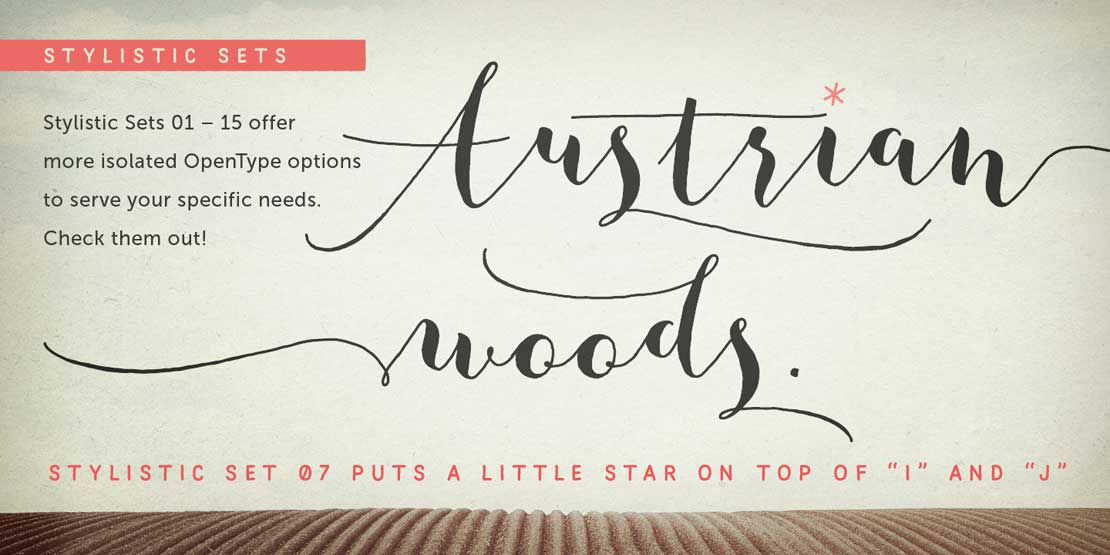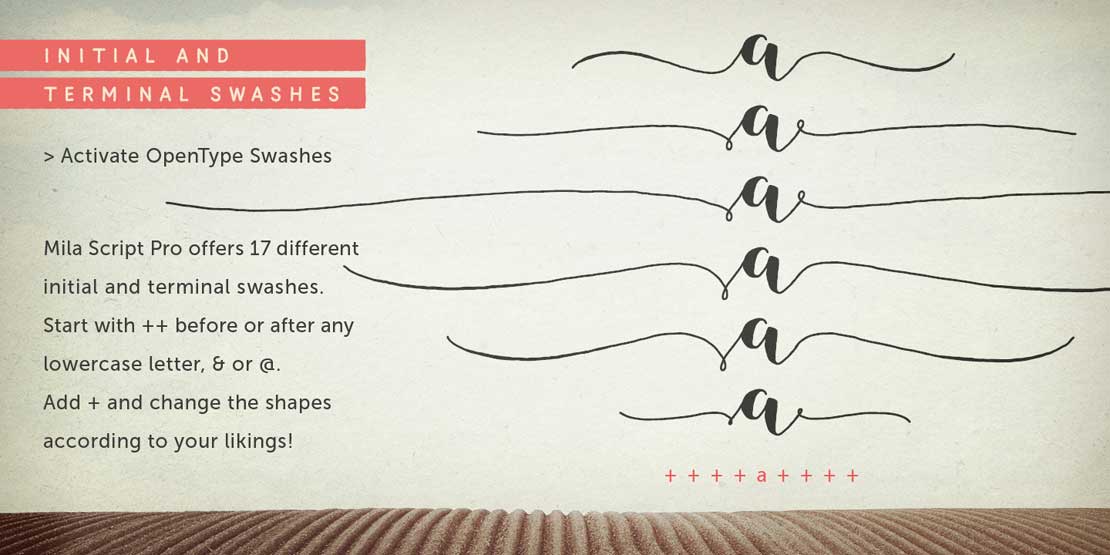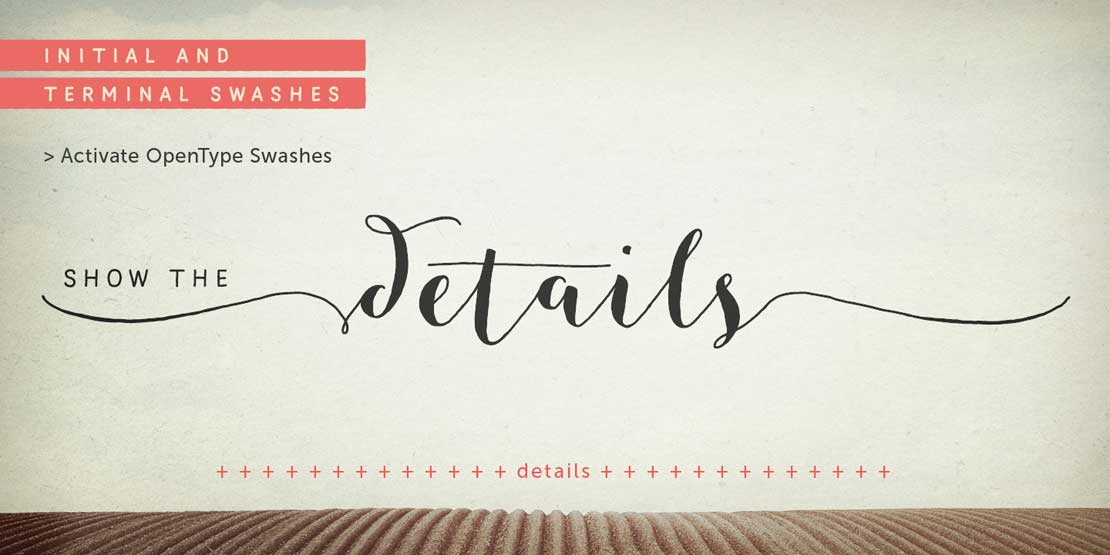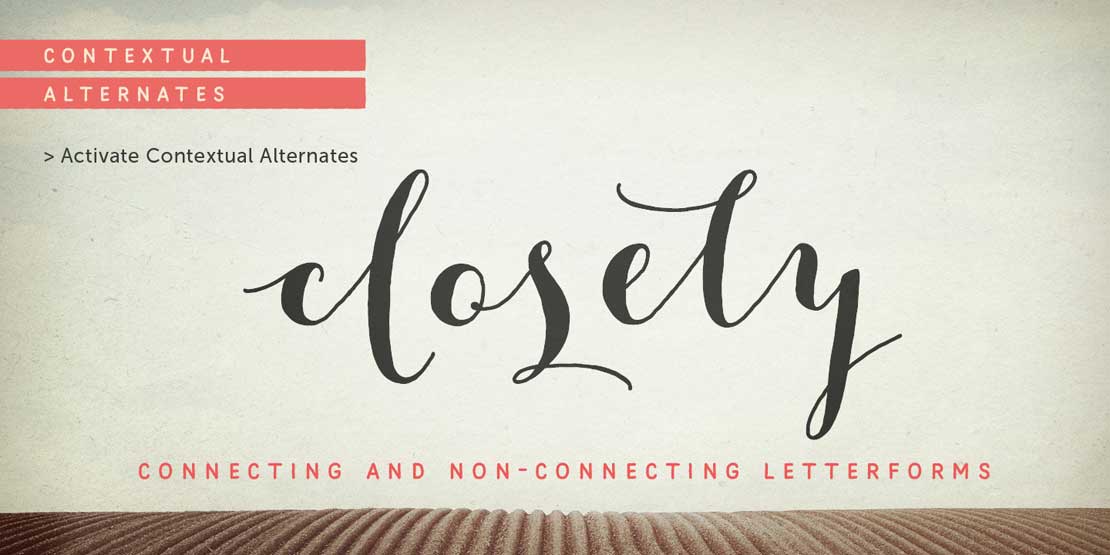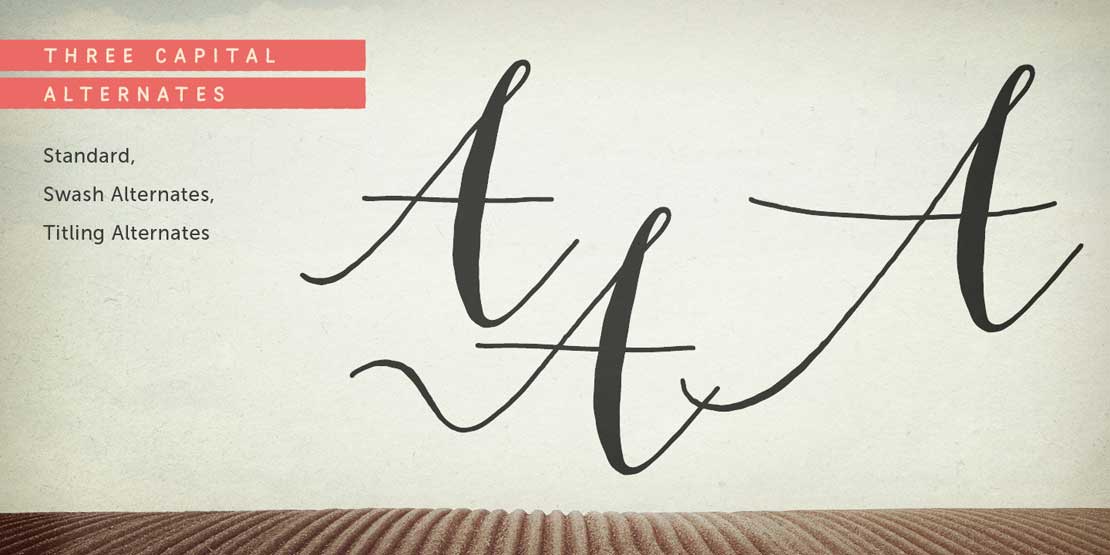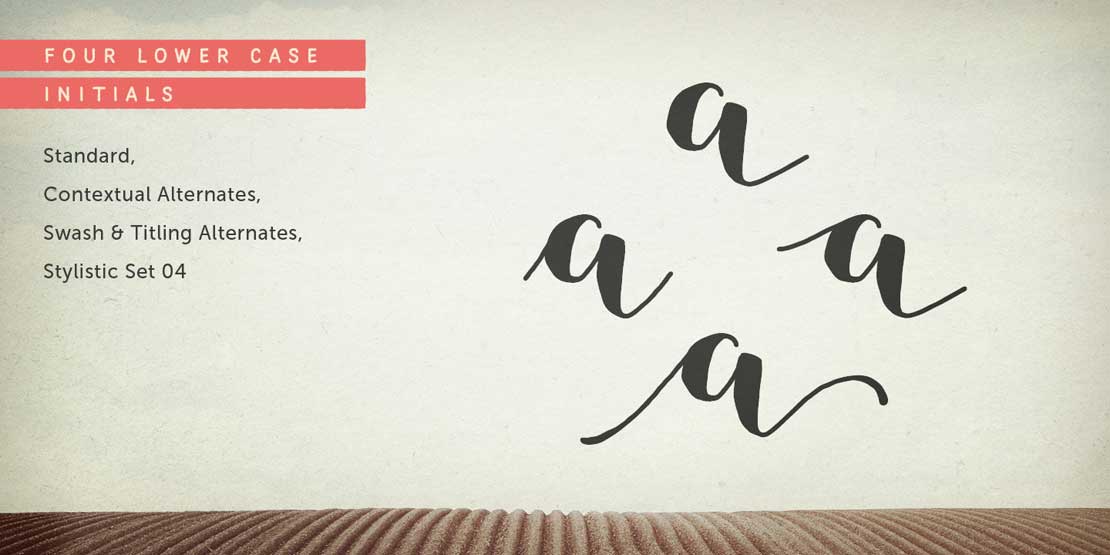
Schwungvolle »Mila Script Pro«
Der Wiener Typedesigner Georg Herold Wildfellner hat seine neue Schreibschrift »Mila Script Pro« veröffentlicht. Die schwungvolle Familie bietet viele OpenType-Features und zusätzliche Funktionen.
Über 2.600 Zeichen umfasst die »Mila Script Pro« – darunter findet man Nützliches wie Schwungschrift, Titelschriftvarianten, Bedingte Ligaturen, Formatvarianten und viele Formatsätze, die für viele Variationen im Schriftbild sorgen. Das kleine »a« gibt es zum Beispiel in 10 Varianten und das »d« liegt in 54 Versionen vor.
Der Clou an der Vielfalt: die Schrift entscheidet selbst, welche Variante gerade am besten passt. Wortanfang und Wortende lassen sich mit 17 verschiedenen Schwüngen betonen und automatisch mit den Kleinbuchstaben verbinden. Auch einzelne Worte können miteinander in 10 Varianten zusammengesetzt werden.
»Mila Script Pro« und »Basic« unterscheiden sich hinsichtlich der Ausstattung der OpenType-Features. Die Basic-Version mit etwas mehr als 900 Glyphen bietet dezente Schwünge, Positionalformen, Ligaturen sowie eine Auswahl von verbundenen und nicht verbundenen Glyphen.
Zur Schriftfamilie gehört auch der handgezeichnete Versalfont »Mila Script Sans« in den drei Schnitten Light, Regular und Bold. Mit ihm lässt sich Text auch negativ setzen. Außerdem gibt es Alternativen mit gefüllten Punzen. »Mila Script Ornaments« ergänzt die Familie mit 69 verschiedenen Schwüngen und Symbolen in sieben verschiedenen Größen.